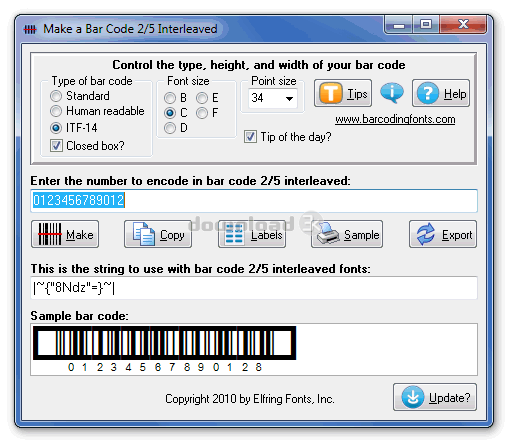
"Print bar code 2/5 interleaved from Windows"
Imprimez votre propre code barres 2/5 entrelacé ou ITF-14 à partir de nimporte quel programme Windows! Cette TrueType évolutives et un ensemble de polices PostScript permet de pratiquement tous les codes à barres dimpression du programme Windows existants. Code barres 2/5 entrelacé est un code numérique densité élevée de bar, nexige pas une somme de contrôle, et vous permet de coder les nombres seulement (vous devez avoir un nombre pair de chiffres.Ce paquet de code à barres contient 20 polices. Ces polices comprennent à la fois une norme (codes à barres seulement) et A (codes à barres avec du texte ou des numéros ci-dessous) lisibles versions de code barres 2/5 entrelacé. Les codes à barres viennent aussi avec et sans barres au porteur. Chacun de ces types de codes à barres est disponible en cinq formats dimage différents, de sorte que vous pouvez faire varier la hauteur et la largeur des barres indépendantes les unes des autres. Cela vous permet dimprimer des codes barres avec la même hauteur, mais avec la barre dépaisseurs différentes.
Notre logiciel vous permet dimprimer vos propres codes à barres sur vos documents et emballages, ou vous pouvez imprimer des feuilles détiquettes avec code à barres 2/5 en utilisant notre utilitaire Bar25i. Ce programme peut même exporter votre code à barres comme un gif, jpg, png ou. Vous voulez imprimer des codes à barres dans Access ou Excel? Nous incluons des fonctions de macro Visual Basic qui font tout le travail pour vous. Si vous ne comprenez pas les codes à barres, il suffit dexécuter le programme utilitaire Bar39 (inclus dans ce forfait) pour construire des codes à barres pour vous. La version de téléchargement inclut un manuel en format RTF compatible avec nimporte quel traitement de texte Windows. Le paquet physique vient sur CD avec un manuel imprimé.